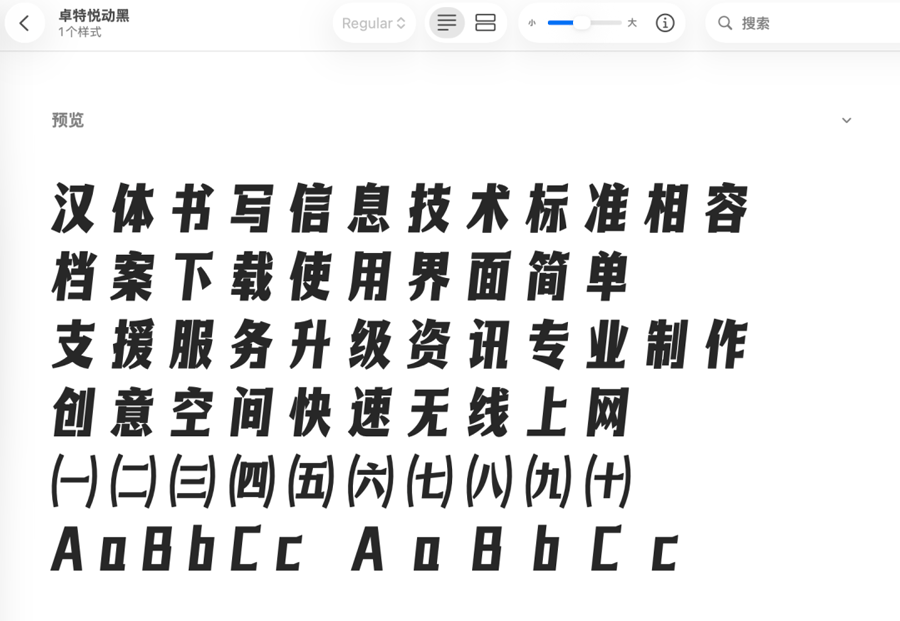
卓特悦动黑是由卓特视觉与字体设计师刘兵克合作开发的一款免费可商用的黑体字体,主打力量感、动感与复古风格。
整体字形瘦长挺拔,并带有轻微的向右倾斜角度,自带强烈的动感与速度感。笔画粗壮坚实,横画末端还带有独特的尖角装饰,视觉冲击力极强。非常适合需要醒目、吸睛、有力量感的标题场景,但不建议正文排版(笔画过粗、阅读性差)。